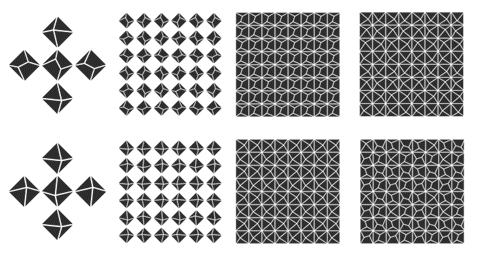
Priori Acute, de Jonathan Barnbrook, es una tipografía experimental con el toque de perspectiva imposible de M.C. Escher. El efecto es tan sutil que hay que mirar cada letra para entender bien lo que está sucediendo en todo su esplendor.
Como bonus se incluyen en algunos caracteres unos ornamentos escherianos que forman interesantes patrones repetitivos.